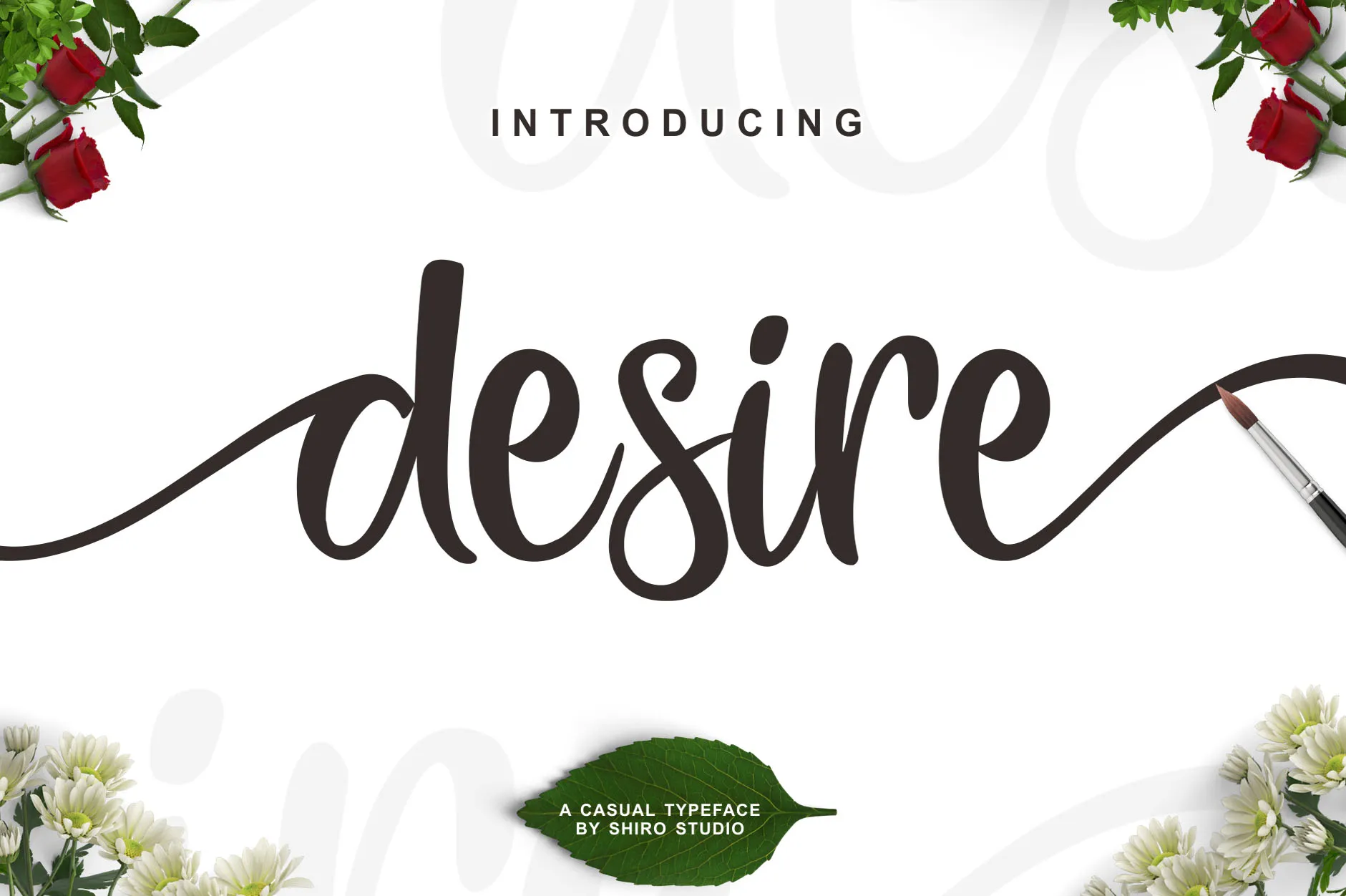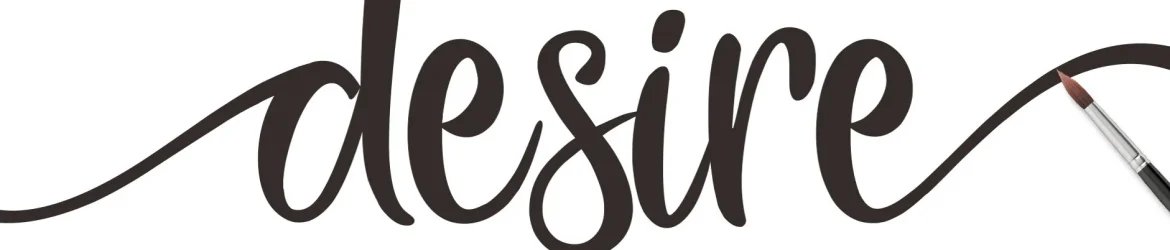
Desire Script Font – Download Grátis
A Desire Script Font é uma tipografia inspirada no estilo do calligrafista, com linhas elegantes e sutis que se tornam perfeitamente adaptáveis para uso comercial. Esta fonte foi criada por um designer de tipos, oferecendo um conjunto único e sofisticado de letras. Para quem está interessado em adquirir uma licença comercial desta fonte, a Desire Script é o tipo perfeito para estilos escritos manuscritos ou para criações gráficas que exijam um ar mais delicado e elegante. Quando se trata de incorporar esta fonte no seu trabalho, ela é perfeita tanto para aplicações comerciais quanto para uso pessoal. Os resultados são sempre profissionais e sofisticados, sem perder o encanto e a personalidade que cada letra do tipo original tem. Seja você um designer gráfico ou ilustrador, esta fonte traz uma nova dimensão ao seu trabalho.